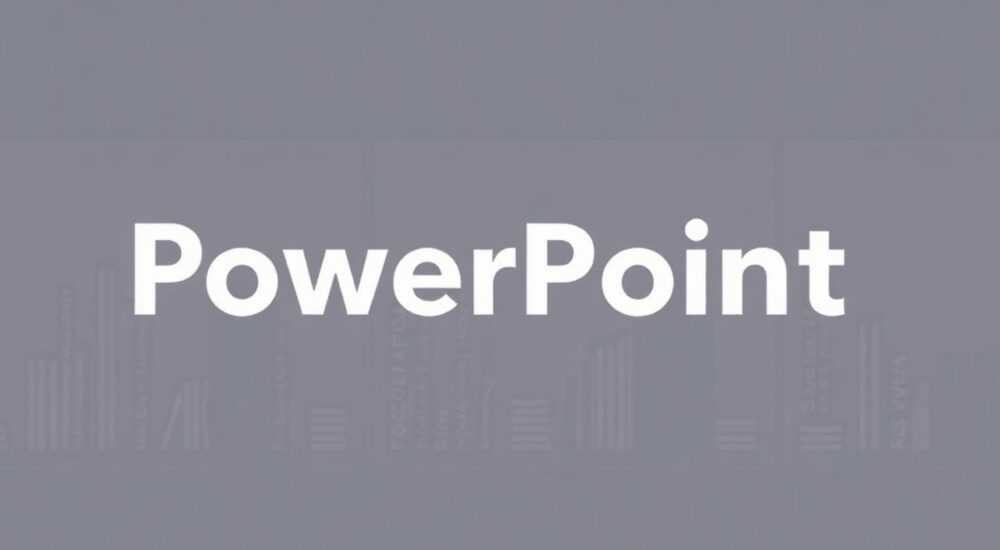
Какой шрифт выбрать для презентации powerpoint
Создание эффективной презентации в PowerPoint — это не только про содержание слайдов, но и про их внешний вид. Шрифт играет ключевую роль в восприятии информации: он может сделать текст читаемым и профессиональным или, наоборот, вызвать раздражение и отвлечь аудиторию. Неправильный выбор шрифта способен свести на нет даже самую сильную идею. Поэтому важно понимать, как подобрать оптимальное начертание, учитывая контекст выступления, тип аудитории и технические особенности отображения.
Основные требования к шрифтам для презентаций
При выборе шрифта для презентации в PowerPoint нужно ориентироваться не на личные предпочтения, а на функциональность. Основная задача — обеспечить максимальную читаемость текста при минимальных усилиях со стороны зрителя. Особенно это важно, если презентация показывается в большом зале, где часть аудитории находится далеко от экрана.
Шрифт должен быть универсальным: хорошо смотреться как на компьютере, так и на проекторе, на разных типах экранов — от офисного монитора до конференц-залового экрана. Важно также учитывать совместимость. Если вы передаёте презентацию коллеге или заказчику, шрифт должен корректно отображаться на его устройстве.
Существует два основных типа шрифтов: с засечками (serif) и без засечек (sans-serif). Для цифровых презентаций предпочтительны sans-serif — они легче читаются на экранах, особенно при небольшом размере или низком разрешении. Засечки могут «дрожать» или теряться на проекторе, создавая визуальный шум.
Когда использовать serif, а когда sans-serif
- Sans-serif (без засечек) — идеальны для заголовков и основного текста в PowerPoint. Примеры: Arial, Helvetica, Calibri, Segoe UI. Хорошо масштабируются и читаются на любых экранах.
- Serif (с засечками) — подходят для печатных материалов, но в цифровых презентациях их стоит использовать осторожно. Иногда допустимы в заголовках, если стиль презентации требует классики и строгости (например, юридические или академические темы).
Лучшие шрифты для PowerPoint: обзор и сравнение
PowerPoint по умолчанию предлагает несколько системных шрифтов, которые уже оптимизированы под презентации. Но пользователи часто пытаются заменить их на что-то «красивое», забывая о практичности. Давайте разберём топ-7 шрифтов, которые действительно работают.
Шрифт |
Тип |
Где используется |
|---|---|---|---|---|
Calibri |
Sans-serif |
Шрифт по умолчанию в PowerPoint с 2007 года |
Чёткий, современный, отлично читается на экранах |
Иногда кажется слишком «офисным» |
Arial |
Sans-serif |
Универсальный выбор для деловых презентаций |
Есть на всех устройствах, высокая читаемость |
Слишком распространён, может выглядеть скучно |
Segoe UI |
Sans-serif |
Системный шрифт Windows, популярен в IT-среде |
Оптимизирован для экранов, мягкие формы |
Может быть трудночитаем при маленьком размере |
Helvetica |
Sans-serif |
Дизайн-проекты, креативные презентации |
Профессиональный, нейтральный вид |
Нет на всех ПК, возможны проблемы с совместимостью |
Roboto |
Sans-serif |
Цифровые продукты, стартапы, технологические темы |
Открытый шрифт, хорошая масштабируемость |
Требует установки, не входит в стандартный пакет Office |
Georgia |
Serif |
Академические доклады, литературные темы |
Хорошо читается на экране среди serif-шрифтов |
Не подходит для основного текста в массовых презентациях |
Lato |
Sans-serif |
Креативные и образовательные презентации |
Дружелюбный, открытый характер, бесплатный |
Может быть слишком «лёгким» при плохой подсветке |
Как подобрать шрифт под конкретную аудиторию и тему
Шрифт — это не просто инструмент передачи текста, это часть языка бренда и тональности выступления. Он может говорить о серьёзности, креативности, новизне или традиционности. Поэтому при выборе шрифта нужно задать себе три вопроса: